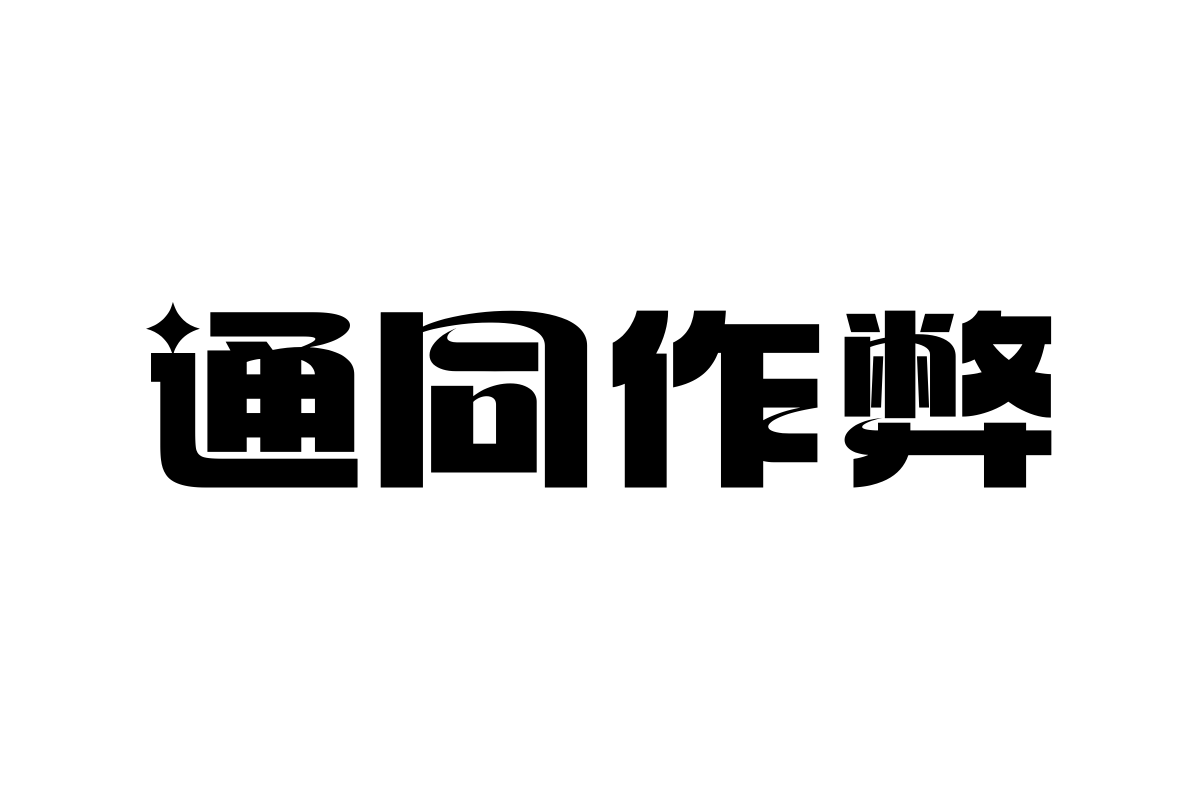
上首潮玩体是一种现代的、时尚的字体,它结合了传统书法和现代设计元素,创造出独特的视觉效果。这种字体的特点是:
1. 字形独特:上首潮玩体的字形设计独特,线条流畅,富有动感,给人一种活泼、年轻的视觉感受。
2. 易于识别:由于其独特的字形,上首潮玩体很容易被人们识别,无论是在印刷品还是电子屏幕上,都有很好的可读性。
3. 适合多种应用场景:上首潮玩体不仅适用于传统的印刷品,如书籍、杂志、报纸等,也非常适合用于现代的设计元素,如广告、海报、网页设计等。
总的来说,上首潮玩体是一种既具有传统韵味又不失现代气息的字体,非常适合用于各种需要表达个性和创意的场合。